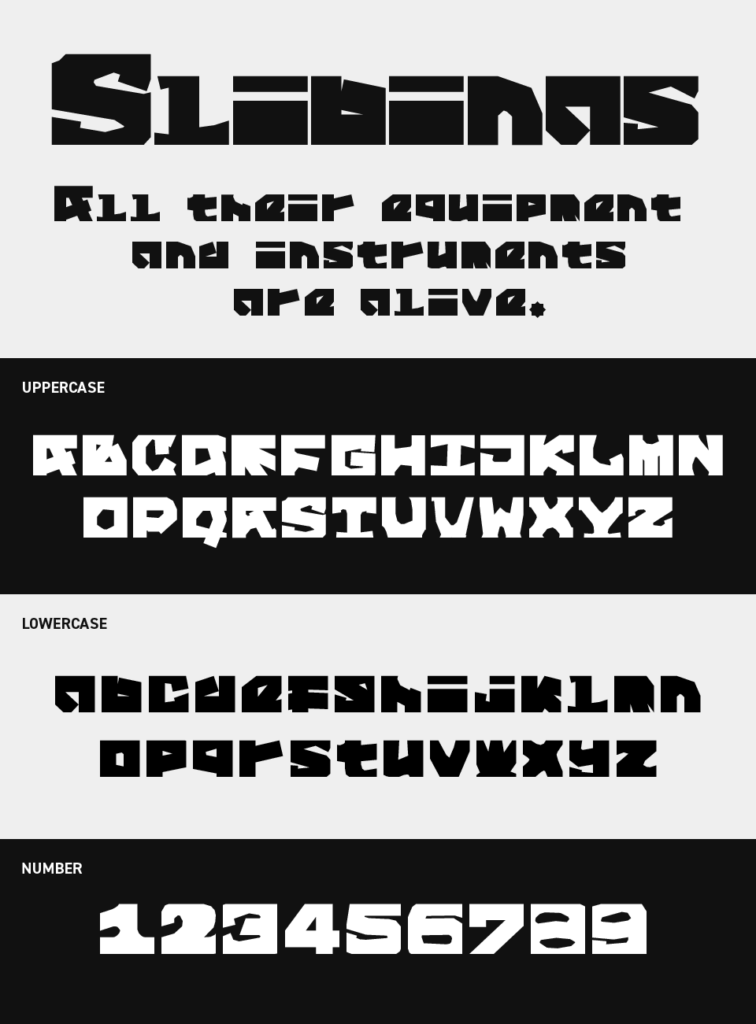
Slibinasフォントは、直線的でブロック感のあるシルエットに、断片的なカットを加えたエッジの効いたデザインが特徴のデザインフォントです。
ブロックを削って作られたようなゴツゴツ感で、角ばったフォルムと大胆な切り欠きが、ストリート感やアニメ感を強調しています。
アニメタイトルやストリートカルチャー、ゲーム系ビジュアルなど、前面に出したい場面にぴったりなフォントです。インパクトを重視したタイトルやロゴ制作で存在感を発揮するフォントです。